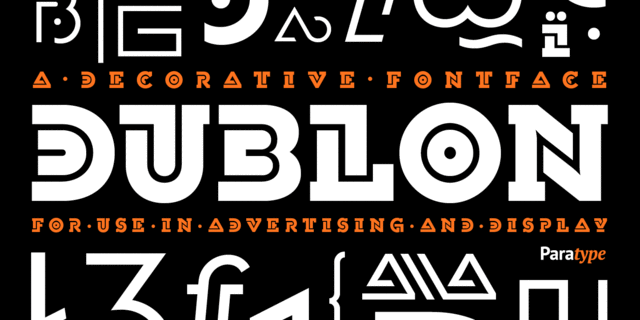
Гарнитура разработана для фирмы ParaType в 1999 на основе оригиналов шрифта украинского дизайнера-графика Олега Карпинского (Винница). Предназначен для применения в рекламе и акциденции.